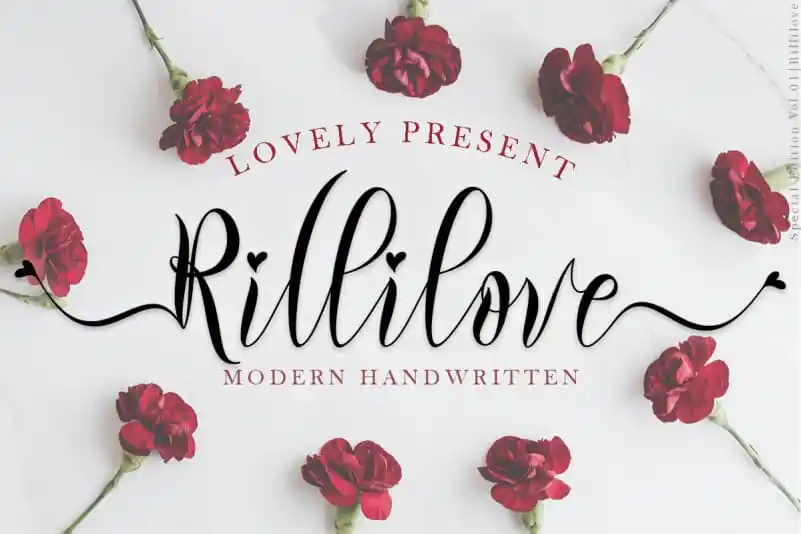
Rillilove Calligraphy Font – Download Grátis
Esta fonte chama-se Rillilove Calligraphy Font. Ela é uma criação cheia de amor do designer Yoga Letter. Desenvolvida com cuidado e atenção aos detalhes, essa font se destaca pela sua beleza refinada e elegância. Seu formato elegante torna a Rillilove uma escolha ótima para qualquer projeto que valorize um toque delicado e sofisticado. É perfeita para anúncios pessoais, marketing de produtos, criação de logotipos ou marcas, inclusão em cartões de convite e mensagens personalizadas. Além disso, a fonte se adequa perfeitamente para momentos especiais como casamentos, ocasiões festivas e atualizações constantes nas redes sociais. Com essa fonte na sua coleção, pode ter certeza de que seus projetos sempre estarão impecáveis e elegantes.